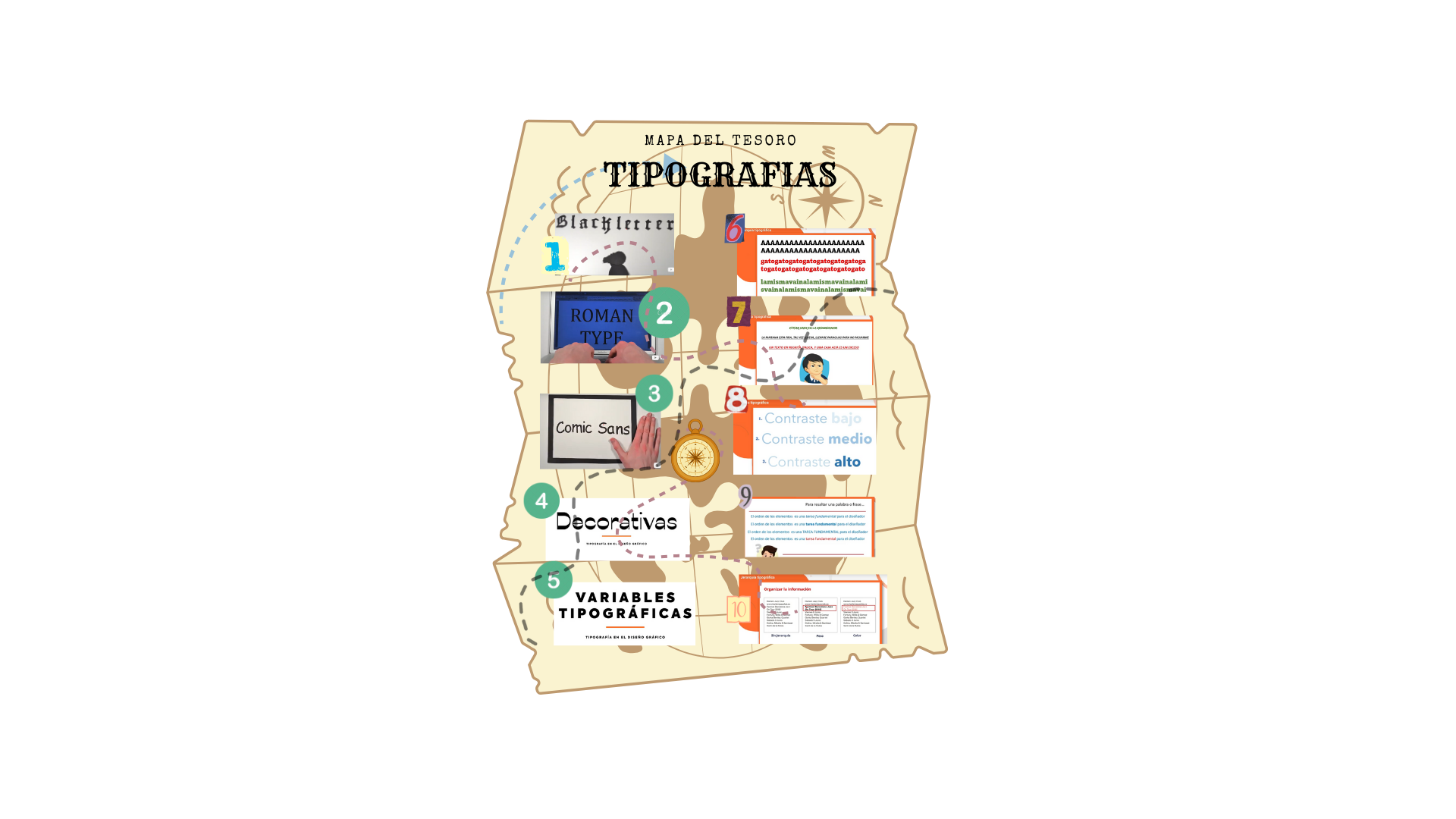
Mapa del Tesoro de la Tipografía
En este mapa interactivo descubrirás conceptos esenciales de tipografía como jerarquía, contraste, variables tipográficas, familias clásicas y errores comunes a evitar. Cada punto del mapa representa un estilo o principio tipográfico, explicado de forma breve y clara para guiar tu aprendizaje en diseño gráfico.
1 Tipografía Blackletter 2 Tipografía Romana 3 Tipografia Comic Sans 4 Tipografías Decorativas 5 Variables Tipográficas 6 Jerarquía Tipográfica 7 Evitar Redundancia 8 Contraste Tipográfico 9 Orden de Elementos 10 Errores de Jerarquía
Explicación
Alto contraste: elegante pero menos legible en tamaños pequeños. Medio contraste: balanceado y versátil. Bajo contraste: simple y fácil de leer en párrafos largos.”